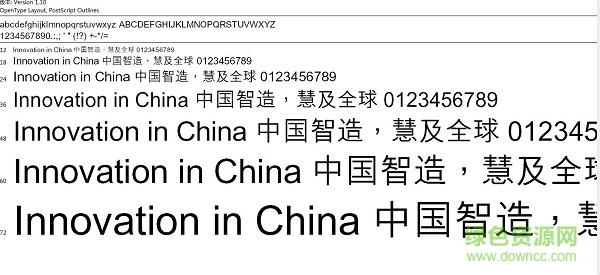
mheigb5-medium字體又叫蒙納簡中黑體,筆畫均勻左右十分對稱,極具美觀性,整體給人以莊重、規(guī)范的感覺,可以用作廣告字體,需要黑體字體的朋友快來免費(fèi)到綠色資源網(wǎng)下載吧!
字體的粗細(xì),英文用Weight一詞表示,越粗的字Weight就越“重”。Weight的各種具體表 示方法從細(xì)到粗一般有:ExtraLight、Light、Regular、Bold、Extra Bold、Black等,不過這些表示 法并沒有統(tǒng)一的標(biāo)準(zhǔn),而且各Weight之間的比例關(guān)系亦因字體而異!
黑體比較端莊嚴(yán)肅、筆畫簡單、結(jié)構(gòu)嚴(yán)謹(jǐn)、引人注目、具有渾厚凝重的氣氛,是印刷界中較為穩(wěn)重、醒目的標(biāo)題字,實用性很強(qiáng)!